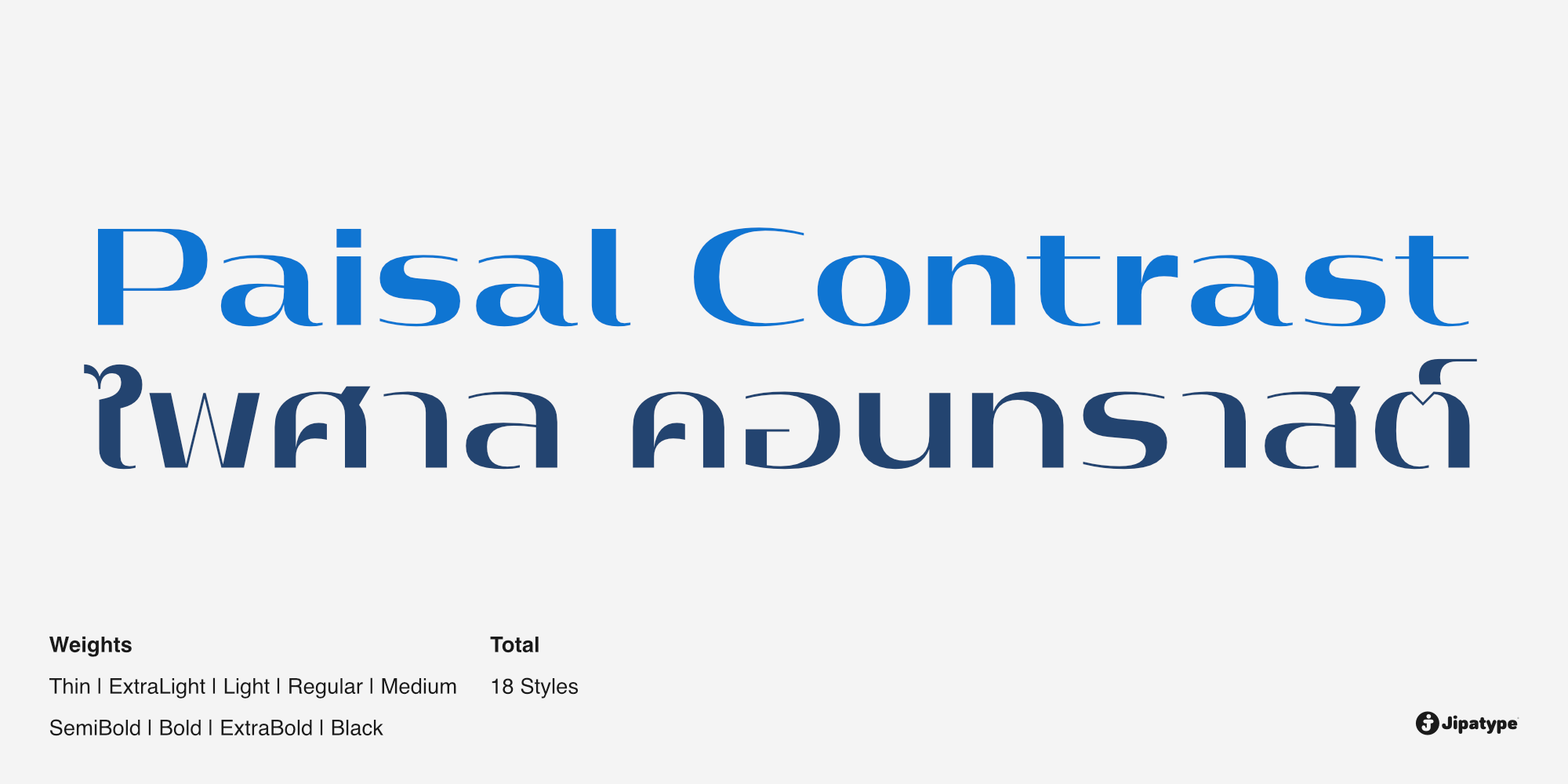
ไพศาล คอนทราสต์ | Paisal Contrast
ชื่อฟอนต์ : ไพศาล คอนทราสต์ | Paisal Contrast
แบบอักษร Paisal Contrast เป็นตระกูลอักษรแบบแซนเซอริฟ ที่ได้รับการพัฒนาต่อยอดจากแบบอักษร Paisal โดยมีการเพิ่มความเปรียบต่างให้กับโครงสร้างตัวอักษร ส่งผลให้แบบอักษรนี้มีลักษณะที่แสดงถึงความหรูหราและความงดงาม แบบอักษรนี้ประกอบด้วย 18 รูปแบบ ครอบคลุมตั้งแต่น้ำหนักเส้นบางที่สุดไปจนถึงหนาที่สุด โดยรองรับทั้งชุดอักษรลาติน 1 และอักษรไทย แบบอักษร Paisal Contrast เหมาะสำหรับการใช้งานในสิ่งพิมพ์ต่าง ๆ ทั้งในรูปแบบออนไลน์และออฟไลน์ และเหมาะสำหรับนำไปประยุกต์ใช้ในงานออกแบบที่ต้องการสื่อถึงความสวยงาม
ผู้สร้าง : อานุภาพ ใจชำนาญ